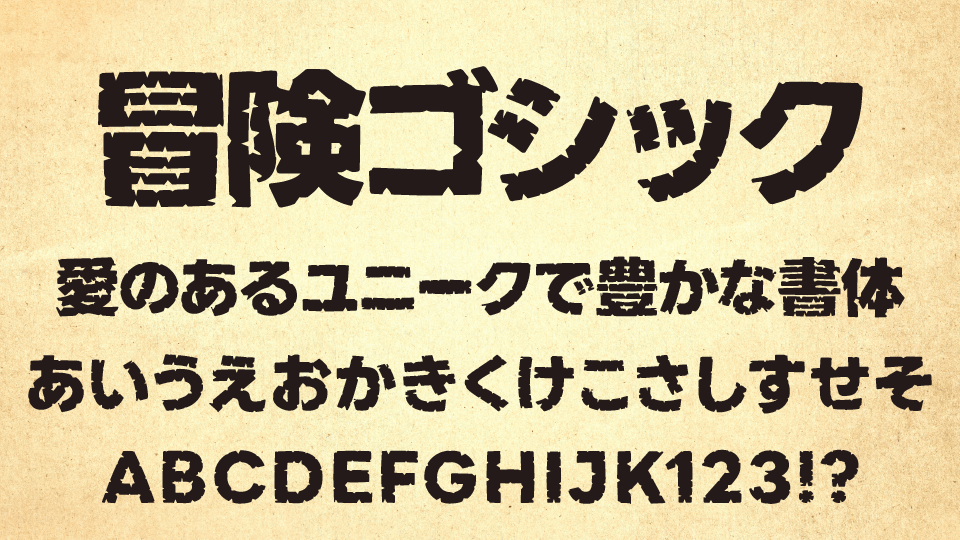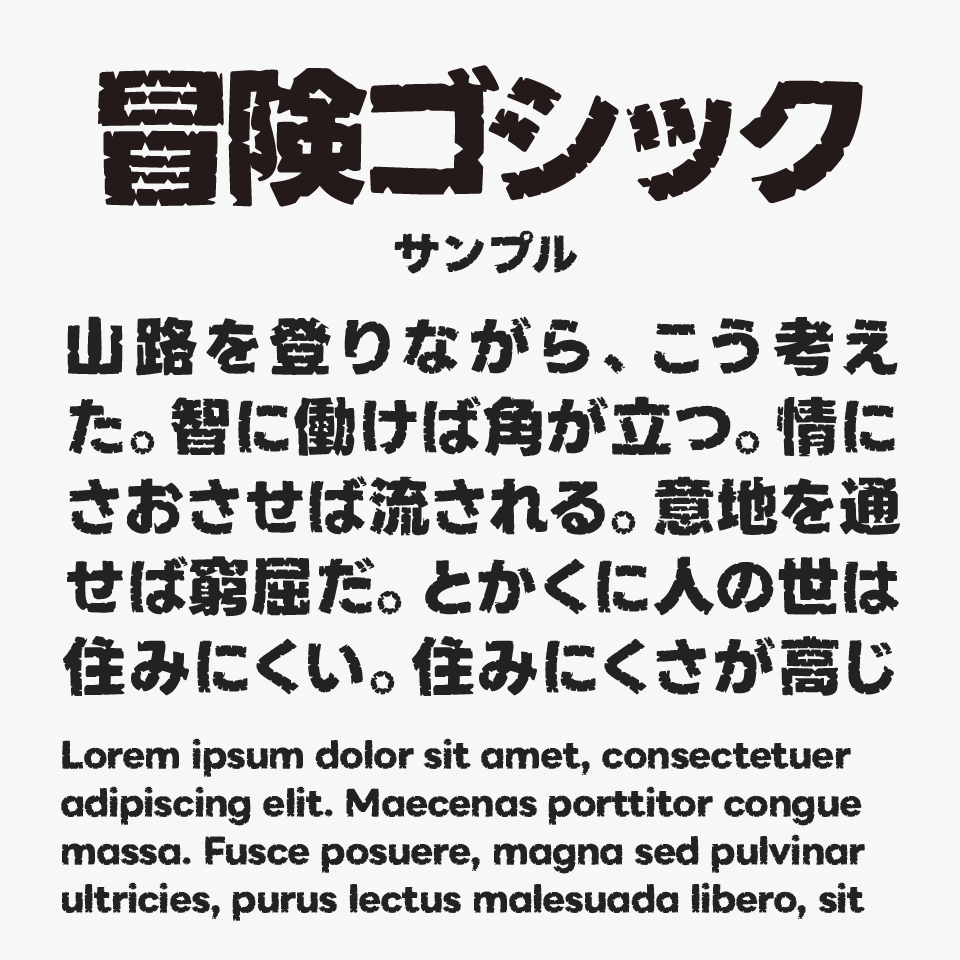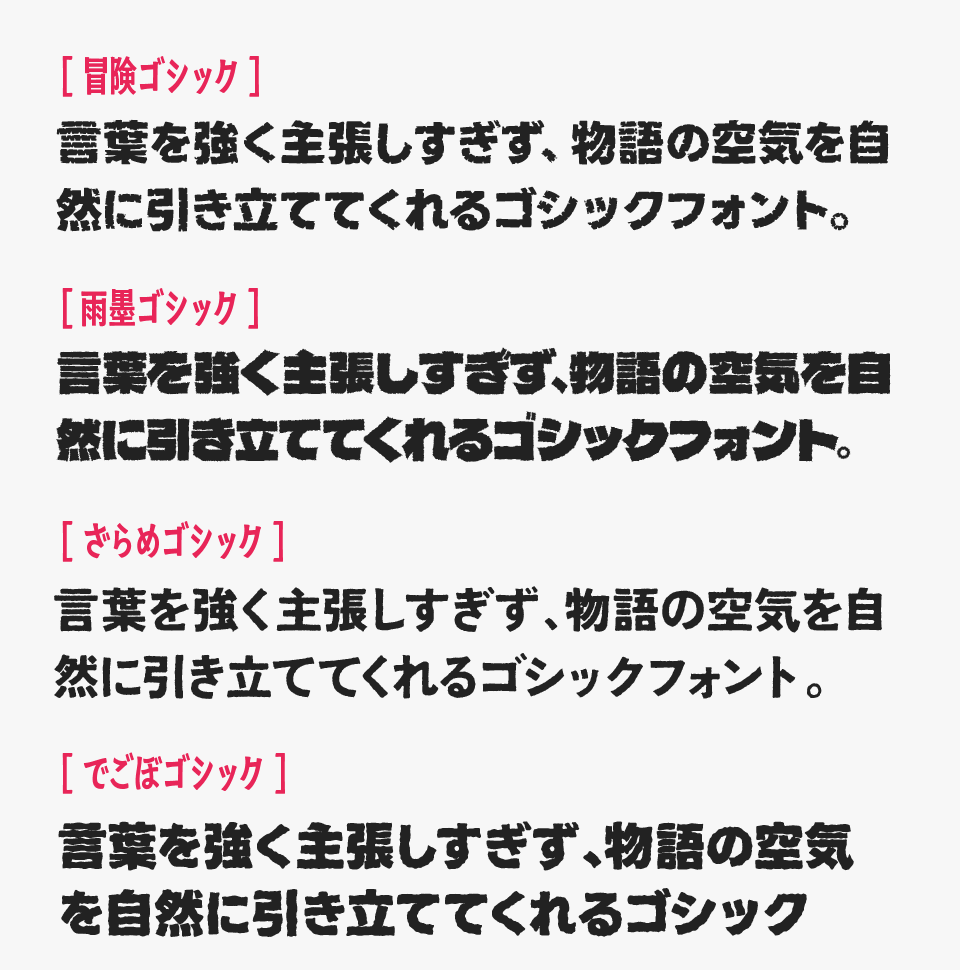
冒険ゴシック
冒険ゴシックフォントは、LINE Seedフォントをベースに、どっしりとした極太ゴシック体に、傷や欠け、ラフな輪郭加工を施したデザイン系ゴシックフォントです。
長い旅路で刻まれた傷跡のような質感が加わることで、力強さの中に冒険の歴史や物語を感じられるデザインです。読みやすさを保ちながらも無骨な存在感があり、タイトルやロゴで印象的なアクセントを生み出してくれるようなフォントです。
ファンタジー作品やRPG、冒険をテーマにしたゲーム、YouTubeサムネイル、イベントロゴなどにぴったりなフォントです。ワクワクする世界観や未知への期待感を表現したい場面で、作品全体の雰囲気をぐっと盛り上げてくれます。
冒険ゴシックフォントを、ほかのかすれた質感をもつフォントと比較してみると、汚れや経年変化を表現することを目的としたデザインとは異なり、冒険の途中で刻まれた傷跡のような加工が特徴のフォントです。